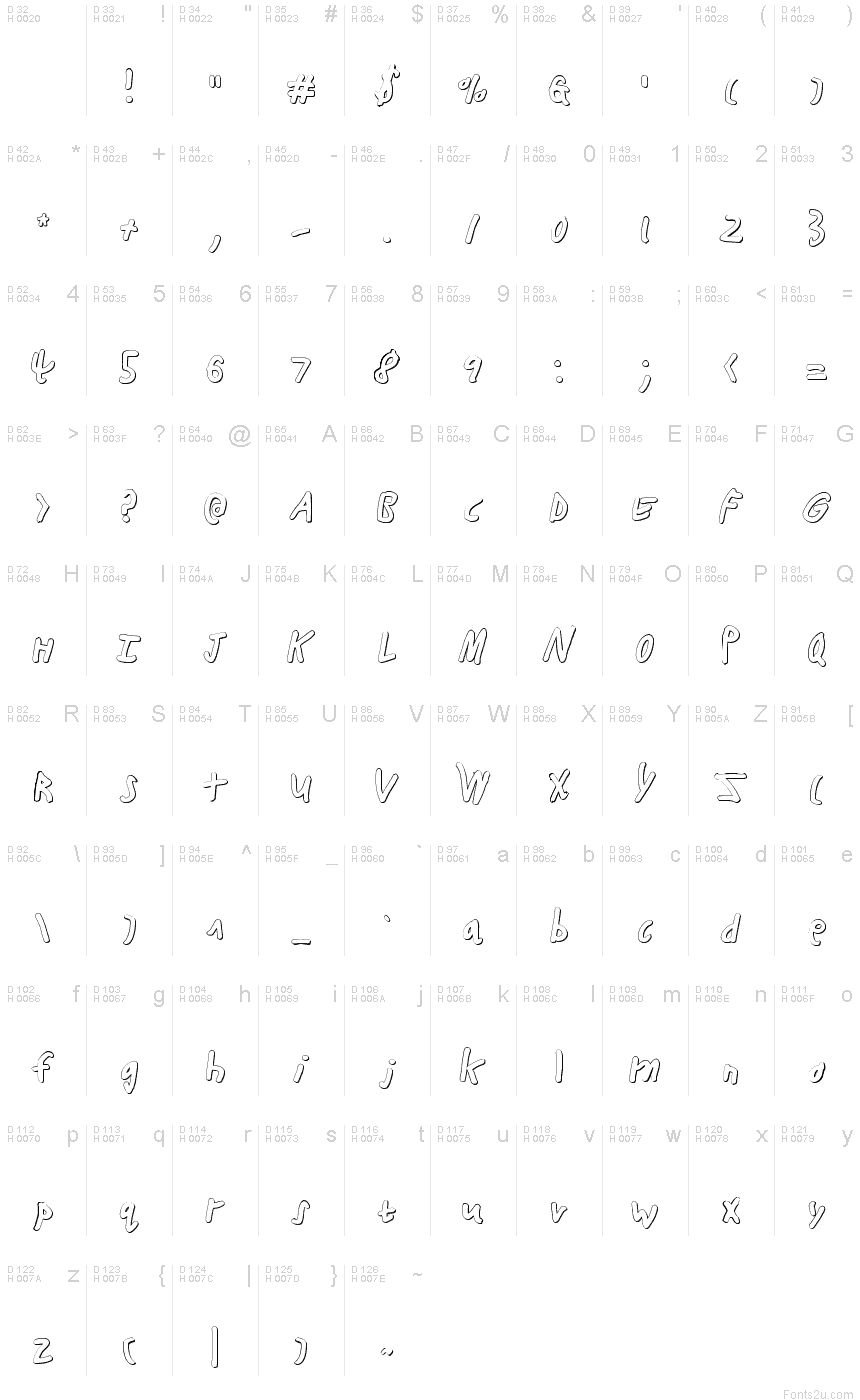
Buttons the Bear 3D to darmowy, konturowy krój pisma odręcznego od Iconian Fonts, wydany w 2008 roku. Dzięki grubym, lekko nieregularnym literom, font zyskuje zabawny, kreskówkowy charakter. Delikatne przesunięte cienie nadają zaokrąglonym kształtom prosty efekt trójwymiarowości, a nierówne kontury podkreślają ręcznie rysowany styl.
Ten darmowy font świetnie sprawdzi się na okładkach książek dla dzieci, opakowaniach zabawek, zaproszeniach na urodziny, tytułach komiksów czy radosnych plakatach szkolnych. Szerokie kształty i dynamiczny rytm sprawiają, że idealnie nadaje się do krótkich nagłówków i haseł, gdzie konturowa konstrukcja ma przestrzeń, by się wyróżnić.
Buttons the Bear 3D